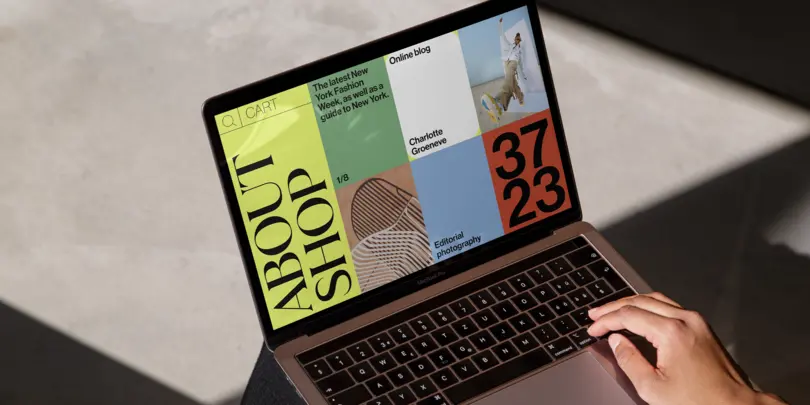
Por qué la transformación digital ha cambiado las expectativas de marca del cliente.
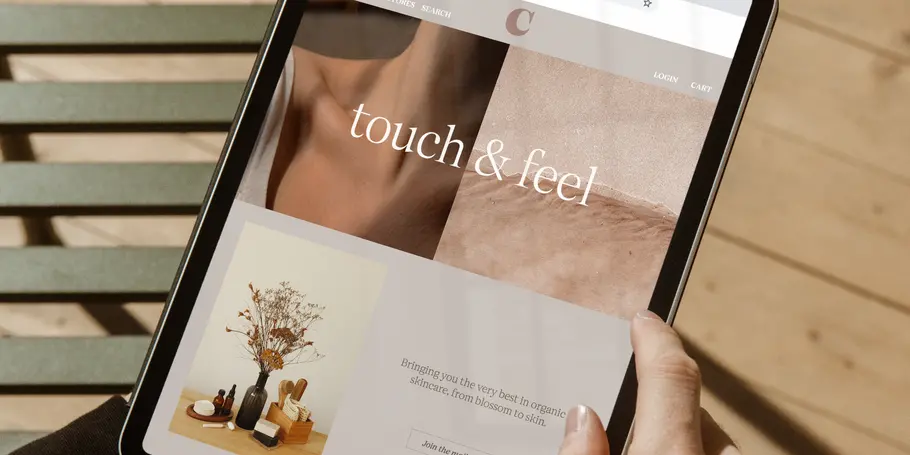
En los últimos diez años, la transformación digital ha influido de forma muy significativa el diseño. Hemos sido testigos de cómo las marcas han pasado de centrarse en vender a contar historias, y el diseño se encarga de narrarlas.
Hace tiempo, el marketing se basaba enteramente en medios impresos. Sin embargo, el punto de partida ahora es el mundo digital. El 89 % de las empresas han adoptado ya una estrategia empresarial que prioriza lo digital o están pensando hacerlo, y el 91 % tienen en marcha una iniciativa digital de algún tipo.
En el arco narrativo del marketing de identidad de marca , puede decirse que la chispa que prendió el fuego fue el auge de la tecnología, pero todo cambió de verdad con la pandemia del COVID-19. Las nuevas normas sobre distancia social y confinamiento hicieron surgir la necesidad de contar con escaparates digitales y sitios web. Esto dio lugar a nuevas oportunidades para la innovación y la creatividad, pero también a que aparecieran algunos obstáculos.
En un mundo pospandémico, nos enfrentamos a una serie de desafíos en lo que respecta a las expectativas sobre identidad de marca que se exponen a continuación.
Humanizar tu marca de forma digital.
Durante la pandemia, los clientes se hicieron mucho más conscientes del diseño, los valores y la ética de las marcas. Como resultado, estas se han visto obligadas a demostrar sus propósitos de forma digital. Afortunadamente, los equipos de diseño pueden ayudarlas. Entre las opciones que tiene el personal de diseño para experimentar con las últimas tendencias digitales, los tipos de letras se han convertido en uno de los aspectos esenciales de los proyectos de identidad de marca. Elegir una fuente que represente los valores y la ética de tu marca puede ayudar a los consumidores a identificarla y a conectar con ella.
La idea de la disponibilidad ininterrumpida.
Los clientes esperan también una mayor comunicación. Según algunas investigaciones, la voluntad de ayudar ocupa el primer puesto entre lo que se espera de los líderes de marketing. Los clientes quieren que las marcas les respondan y les ofrezcan una forma de comunicarse con ellas digitalmente. Ya sea en un mostrador o con una línea de atención al cliente, el público quiere poder escuchar una voz y mantener un diálogo con las marcas con las que interactúa. Si quieren satisfacer estas necesidades, las marcas se ven obligadas a estar disponibles en todo momento para ajustarse a las expectativas de sus clientes. A la hora de elegir los elementos del diseño de tu marca, escoge una fuente que también sea de ayuda. La que selecciones debe ser funcional y fácil de leer para que puedas comunicarte rápidamente con los clientes. La ventaja de diseñar para la presencia digital es que las actualizaciones pueden completarse más rápido que en el caso del diseño impreso.
Un alcance mundial y local.
Dado que cada vez hay más marcas que se lanzan al mundo digital, la audiencia de este marketing se ha vuelto más internacional que nunca. Por ello, el personal de marketing digital debe trabajar teniendo en cuenta distintas lenguas y si quiere llegar a su mercado mundial. Para comunicarse a una escala tan grande, es importante personalizar tu mensaje según el mercado. Debes comunicar la ética y los valores de tu marca de una forma universal por medio de fuentes que funcionen en todo el mundo. A la hora de incluir tu misión en tu sitio web, debes asegurarte de que el diseño sea compatible. Es importante elegir fuentes que funcionen bien en varios idiomas y que cumplan su cometido en todo el mundo. Lo creas o no, el 95 % del diseño web es la tipografía, y hay estudios que demuestran que las marcas tienen menos de 50 milisegundos para causar una buena primera impresión.
Mejorar continuamente.
Otro desafío es el de estar al día con los continuos cambios en las expectativas de los consumidores. En un mundo digital, las cosas cambian continuamente a medida que se desarrollan nuevas tecnologías, y se espera que las marcas sigan el ritmo de las últimas tendencias. Para adaptarse, es posible que las compañías deban contratar a consultores de redes sociales o aprender nuevas técnicas para no quedarse rezagadas con respecto a la competencia del mercado. Por ejemplo, ahora muchas marcas tienen una aplicación móvil que acompaña a su sitio web digital. Aunque el 85 % de los adultos consideran que el sitio web móvil de una empresa debe ser tan bueno o mejor que el de ordenadores para cumplir con las expectativas de los consumidores, muchas marcas han lanzado también una aplicación móvil. A medida que se lanzan actualizaciones de software, es necesario mantener las aplicaciones para asegurarse de que funcionan correctamente. Hacer estas mejoras continuas ayudará a tu organización a seguir siendo competitiva en el mercado.
Cultivar la fidelidad.
En el mundo digital, reforzar la confianza es clave para crear una base de clientes. Según la encuesta Trust Barometer, el 58 % de la gente comprará a una marca o hablará bien de ella en función de sus ideas y valores. Las marcas tienen que fomentar una sensación de pertenencia y confianza con su audiencia para crear experiencias de cliente duraderas. Centrarse en los elementos del diseño puede ayudar a crear una imagen coherente que fomente esos sentimientos.
Por ejemplo, elegir una fuente que sea coherente en distintas plataformas puede ayudar a crear ese nivel inicial de confianza. Los clientes empezarán a reconocerte y a asociar tu marca con la fuente. Cuando el público ve la tipografía de Verizon, reconoce la marca tanto en la aplicación como en el sitio web, ya que es coherente en todos los canales.
Conseguir que te recuerden.
La mayoría de los estadounidenses ven aproximadamente entre 4000 y 10 000 anuncios al día, por lo que es importante que el sitio, la aplicación y los canales de redes sociales de tu marca tengan un elemento único que ayude a los clientes a recordarte. Piensa en Patagonia, que dedica toda una página de su sitio web a contar sus historias. La marca usa una narrativa fácil de recordar para reforzar sus ideas y valores principales. Si echas un vistazo a sus series de historias, también verás que usan fuentes seleccionadas que se ajustan a la marca para aportar ese toque personal. Es importante crear experiencias positivas a través de tu identidad de marca para que los clientes recuerden los buenos ratos que pasan interactuando contigo.
Accesibilidad.
Por último, pero no por ello menos importante, las marcas deben ser accesibles para todos los usuarios, especialmente porque los usuarios tienen cinco veces más probabilidades de abandonar lo que están haciendo si el sitio web no está optimizado para usarlo en dispositivos móviles. Por ello, la experiencia del sitio tiene que ser óptima tanto en ordenadores como en estos dispositivos. La tipografía debe ser legible en ambos empleando tamaños de fuente adecuados o bien ofreciendo la opción de agrandar el texto.
Las fuentes desempeñan una función fundamental a la hora de ofrecer una buena experiencia de usuario. Una vez que hayas definido los valores principales de tu marca y su misión, puedes aprovechar la tipografía para crear esa relación a largo plazo con los clientes. Entre las soluciones que puedes aplicar está elegir un tipo de letra que se ajuste al tono de tu marca y usar imágenes con las que los clientes se sientan identificados. Independientemente de cuál sea la misión de tu firma, la tipografía es esencial para crear y mantener una relación con los consumidores.